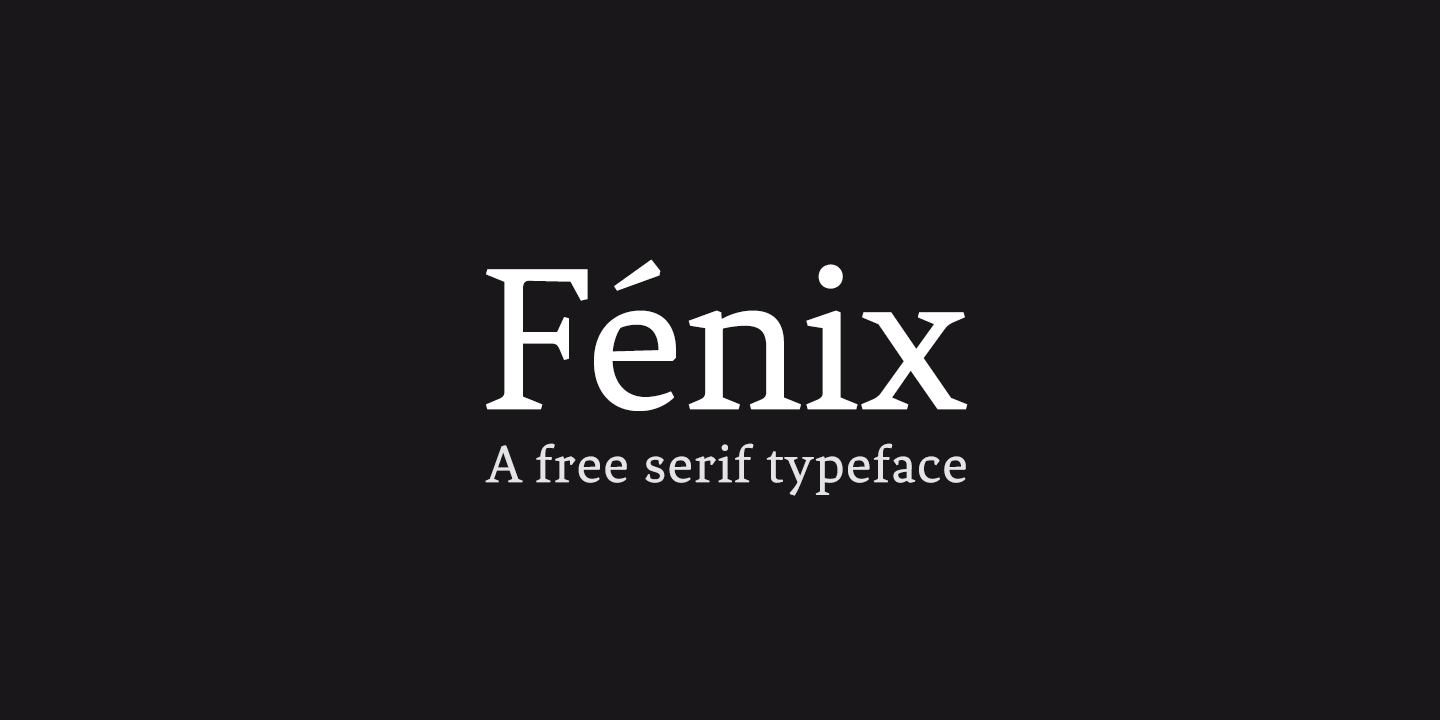
4 повода заказать логотип компании с уникальным шрифтом
Решили заказать логотип компании? Выбирайте только уникальный шрифт.
В последнее время мы постоянно обмениваемся бесчисленным количеством сообщений, мессенджеры заполонили нашу жизнь. Например, у меня в телефоне их 5, и друзья настойчиво рекомендуют поставить еще и шестой. Мы ведем дневники и микроблоги в социальных сетях, регулярно публикуя свои мысли и эмоции в сеть. Но исследования показывают, что сообщения и публикации становятся больше визуальными, нежели текстовыми. И это означает, что наши информационные каналы перегружены, и картинку или видео воспринять гораздо проще, чем написать или прочитать осмысленный текст. Инстаграмм и твиты тому доказательство. И именно этим обусловлена растущая популярность создания инфографики – рай для визуалов.
Но бренды в своих коммуникациях с ЦА, как правило, транслируют нечто большее, чем просто сообщение.
Поскольку люди все чаще и чаще общаются друг с другом, обращаются за советом и ищут информацию через такие социальные медиа, как соцсети, видео обзоры и видео блоги – бренды обязаны держать руку на пульсе и в свою очередь коммуницировать не с абстрактным потребителем, а с личностью!
И напрасно большинство компаний упускают из виду такой прекрасный инструмент как шрифт. А ведь уникальные шрифты, если вы собираетесь заказать логотип компании, могут стать основой формирования индивидуальности и, пожалуй, основным из способов продвижения бренда.
1. Заказать логотип компании с уникальным шрифтом и выделиться среди конкурентов.
Пример использования оригинального шрифта. Хенд леттеринг
Великие бренды отходят от стандартных системных шрифтов, то есть тех, что установлены по умолчанию в компьютере и встроены в графические редакторы, просто потому, что они не отражают их суть, индивидуальность. Сейчас уже мало кому придет заказать логотип компании со стандартными шрифтами.
Цифровые и медиа носители, являются ключевым аспектом в продвижении брендов. Теперь, когда веб сайты уже повсеместно адаптируются под мобильные устройства, каналов для коммуникации с потребителем становится все больше. Но это также влечет за собой создание отзывчивых и понятных интерфейсов, в том числе и в плане шрифтов и продуманной типографики. Также и логотип бренда все чаще появляется в разных контекстах, на различных медиа площадках, и его окружение должно создавать определенный эмоциональный бэкграунд. Уникальный шрифт отлично справляется с этой задачей, вызывая доверие к бренду.
2. Нужно провести ребрендинг — станьте ближе к людям.
Оригинальный шрифт в логотипе
Типографика – это ключ к успешному ребрендингу.
Процесс создания шрифта является сложным и многослойным. С одной стороны типографика должна быть эффективной, то есть правильно разработан шрифт, учтены основные правила, выдержаны интервалы, ширина букв и т.п. С другой стороны шрифт, подобно человеку, должен рассказывать историю бренда, доносить определенное сообщение, демонстрировать различные стороны личности бренда. Такие шрифты успешно коммуницируют на эмоциональном уровне.
Иногда маркетологам хочется заказать логотип компании или провести ребрендинг просто ради шумихи в прессе, ради публикации новости на сайте. Это тоже вариант, но нужно достойно подбирать исполнителей. Подобрав исполнителей, прислушиваться к их профессиональному мнению, и быть аккуратнее в стремлении создать чересчур оригинальное написание.
Неудачный пример ребрендинга. Неоднозначное прочтение логотипа.
3. Дизайн логотипа — как подобрать правильную интонацию.
Каждая шрифтовая гарнитура имеет свою интонацию. Я не буду вдаваться в подробности классификации шрифтов, это тема для отдельной статьи и материалов об этом очень много.
Скажу лишь, что шрифты с засечками — это классика, созданная еще во времена римлян. Засечки гармонично сочетаются с брендами косметики, юридическими компаниями старой закалки, брендами классической одежды, банкам с историей, словом, им подходит все то, что претендует на глубокие корни и солидный опыт. К этой категории относятся гуманистические шрифты, геральды, антиква барокко и брусковая антиква.
Поэтому если вы заказываете логотип компании, основанной в прошлом веке, или ваша компания создана вчера, но вы хотите произвести впечатление умудренных опытом — то использование шрифта с засечками в процессе создания логотипа как раз для вас.
Пример шрифта с засечками стилизованного под русскую кириллицу
Пример классического рукописного шрифта с засечками
Рубленные шрифты
( без засечек) – это новые и старые гротески, гуманистические и геометрические гротески. Вызывают ощущение стабильности, надежности, иногда инновационности.
Рукописные или каллиграфические шрифты
вызывают ощущение ручной работы, живости, натуральности. Часто содержат нарочито неровные элементы, что придает им еще больше уюта и тепла. Идеальны для кафе (меловой леттеринг), пекарен, брендов натуральной косметики, натуральных продуктов питания «только из под коровы» и т.д.
Выбирая нужную интонацию в шрифте логотипа вы закрепляете за своим брендом уникальную нишу. Человек, взглянув на логотип почти сразу понимает, что вы солидны или имеете богатую историю, или натуральность ваше кредо. Остальные рекламные ходы вроде легенды бренда, промо материалов и рассказы продавцов-консультантов лишь подчеркивают сказанное в логотипе.
Геллаган является верным воплощением популярной цитаты: «Простота — высшая форма сложности». Геллаган особо не старается, но все равно выглядит красиво. Он сочетает в себе простоту и смелость для создания элегантного образа. Gellahan отлично подойдет в качестве текста логотипа, фирменного стиля и текста заголовка. Разборчивость, простота и смелость этого шрифта — его преимущество.